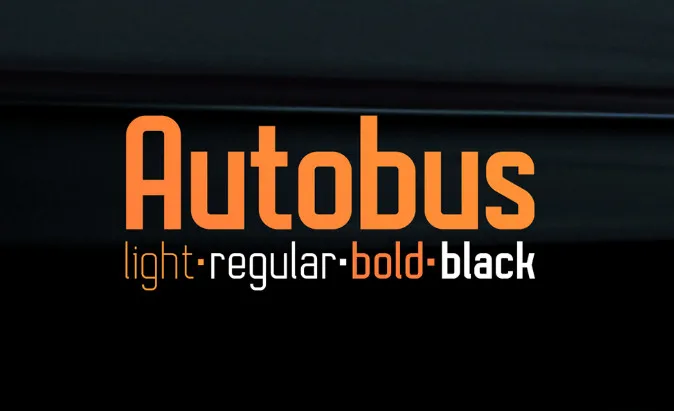
Introduzimos a Autobus Font Family! Desenvolvida e compartilhada pelo NimaVisual, esta familia de fontes sem serif é ideal para quem procura uma solução forte e técnica para os seus projetos de design. Com quatro pesos diferentes e suporte multilinguístico, a Autobus oferece a versatilidade necessária para criar designs eficazes e impactantes. Seja para rótulos, logotipos ou materiais gráficos de jornal, a Autobus está pronta para ajudá-lo a expressar sua mensagem de maneira clara e robusta. Se você busca uma fonte que combina elegância com força, a Autobus pode ser o que você precisa em seu próximo projeto.